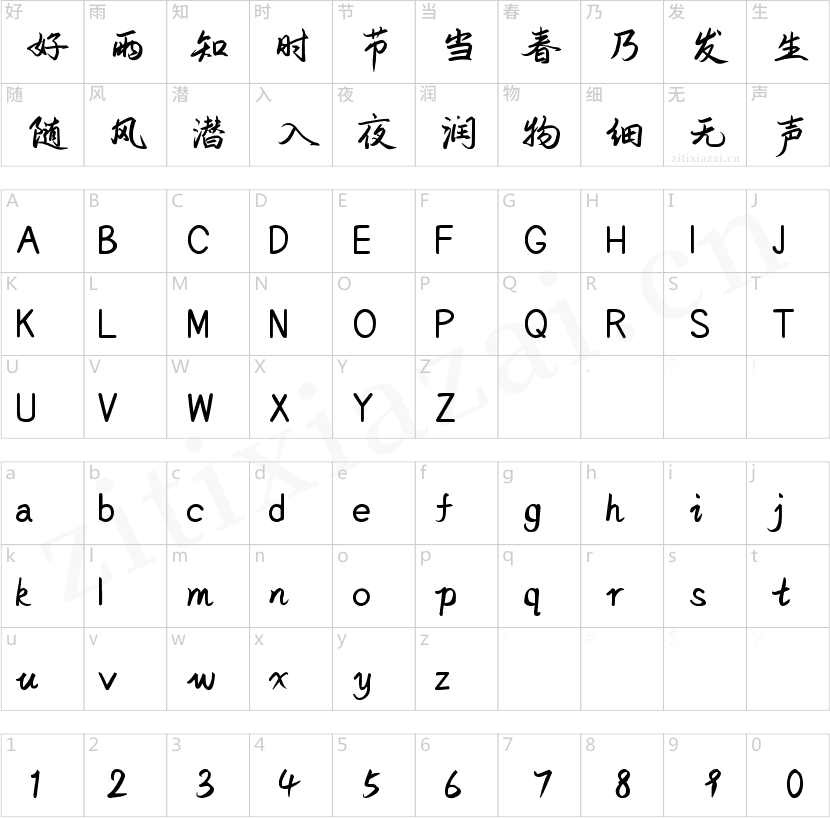
字小魂望书行楷
字魂字体字小魂望书行楷字体是由字魂创意字库设计并生产的一款可商用的字体,被收录于字小魂系列。该字体支持GB-2312标准以及最新的字魂ZH7144标准,包含9498个中文、字母、符号和数字,字体类型偏向毛笔书法,具有中国风的风格,在市面上广泛用于印刷品&包装、电商、排版阅读等场景。